TPフォント使用事例紹介 「広告 その1」
パッケージや書籍、Webサイト、広告など各媒体でのタイププロジェクトのフォントの使われ方を事例を元に紹介していきます。 今回は、広告をご紹介します。
※一部調整されている文字も含みます。
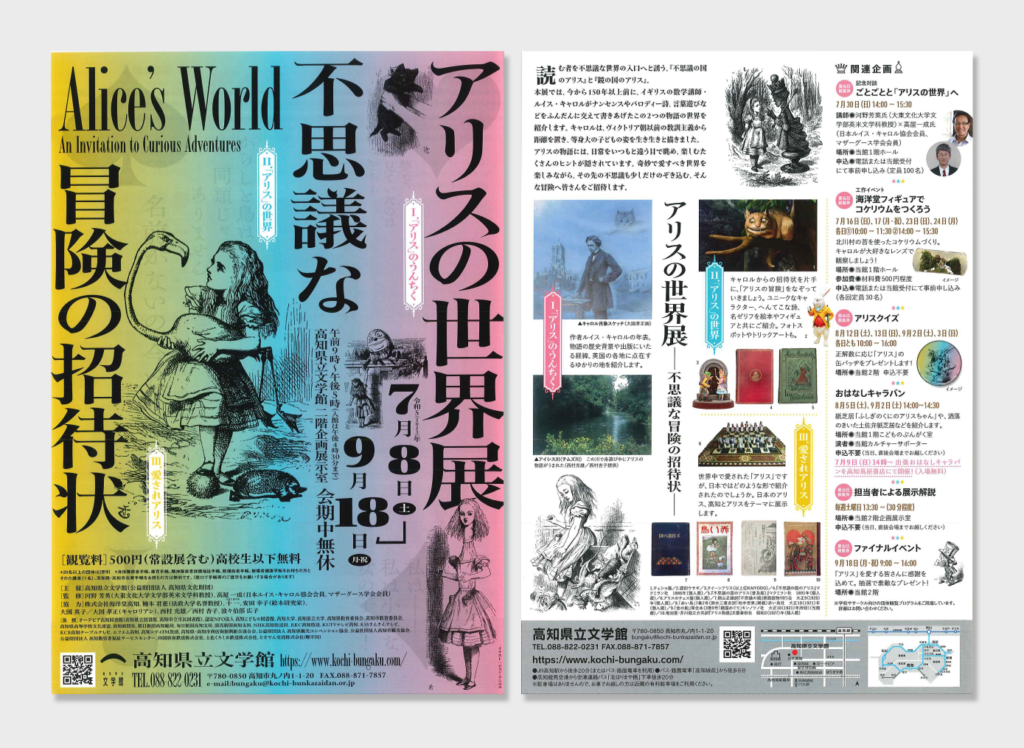
企画展「アリスの世界展―不思議な冒険の招待状―」告知チラシ
広告主:高知県立文学館
【使用されているタイププロジェクトのフォント】
表面・一部裏面:金シャチフォント 姫
高知県立文学館で、昨年開催された企画展「アリスの世界展―不思議な冒険の招待状―」の告知チラシなどの広報物に金シャチフォント 姫が使われています。
ジョン・テニエルのイラストと赤青黄のグラデーション、そして少し平体処理をした金シャチフォント 姫が不思議な世界観を感じさせてくれます。
一般的な明朝体と比べ装飾性が高く、独特のかたちや躍動感のある筆画が特徴の金シャチフォント 姫が和文の多くの部分で使用され、「アリス」の奇妙で愛すべき物語世界の魅力を伝える助力となれているのではないでしょうか。
また、都市フォントプロジェクトのひとつとして、名古屋文化の象徴を取り入れた金シャチフォント 姫が「アリス」の世界とマッチしていることもとても新鮮です。
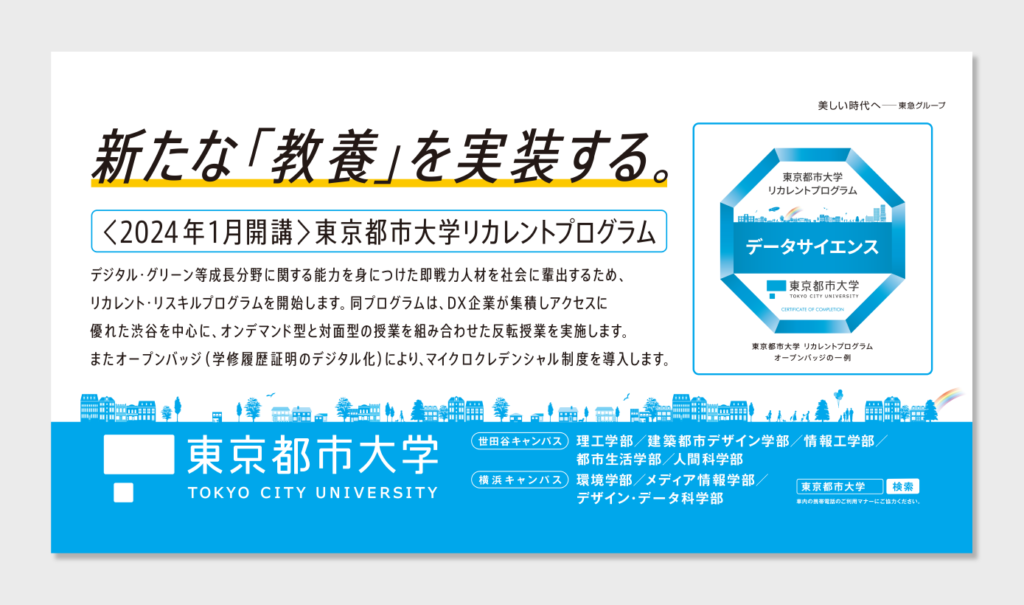
「東京都市大学」電車内広告
広告主:東京都市大学
【使用されているタイププロジェクトのフォント】
キャッチ・リード・ボディーコピー:AXIS Font コンデンス R
東京都市大学の電車内広告のコピー部分にAXIS Font コンデンス Rが使われています。
テキストが主な構成要素ですが煩雑な印象はなく、情報の整理がしっかりとされたデザインとすっきりとした長体フォントで誠実な印象を受けます。
3つの字幅(ベーシック、コンデンス、コンプレス)を持つAXIS Font ファミリーでは、限られたスペースに多くの情報を入れる際に、文字を小さくするのではなく、字幅を調整して対応することができます。その特徴を活かして、この事例ではAXIS Font コンデンスが読みやすさと美しさを担保しつつ情報空間を効率よく活用しています。